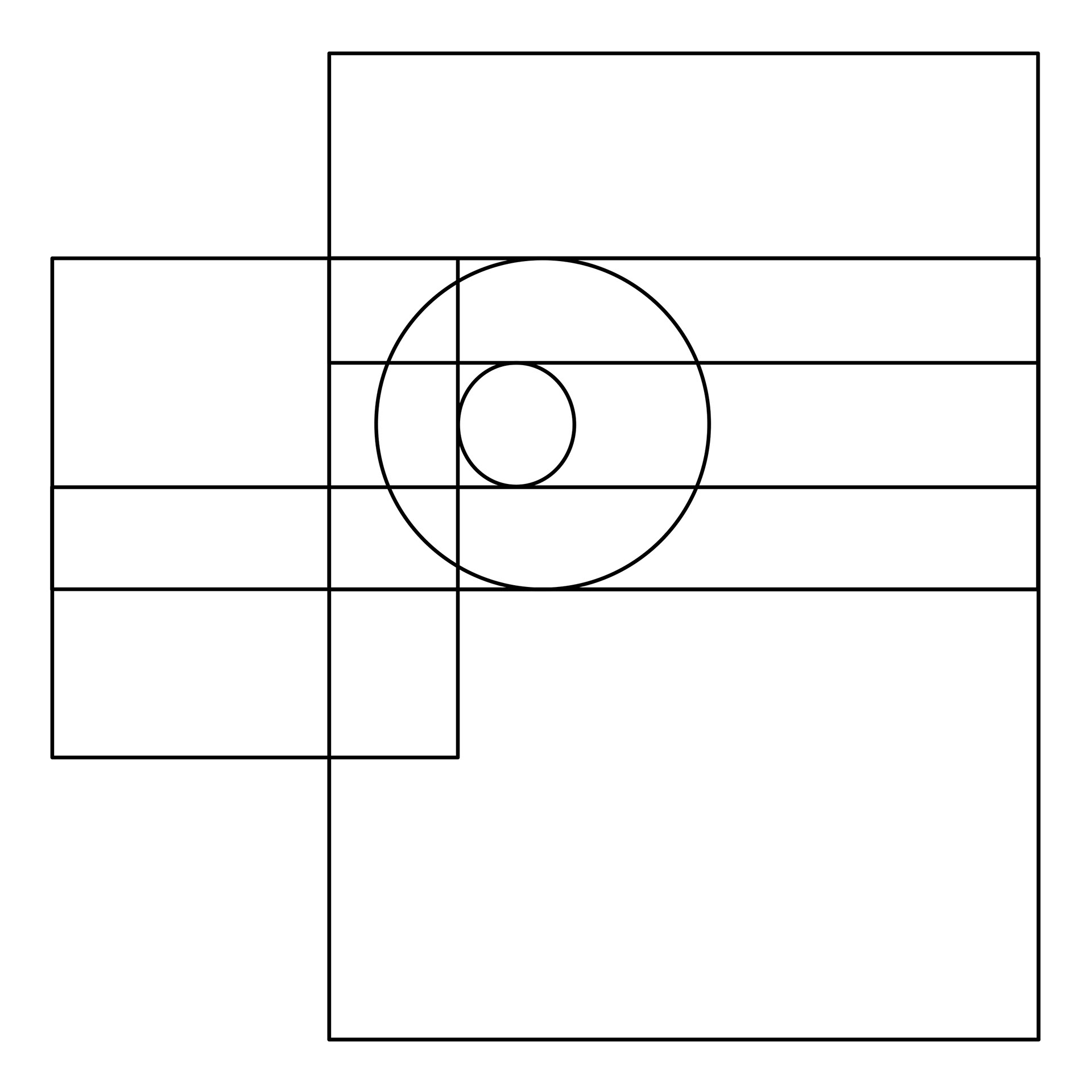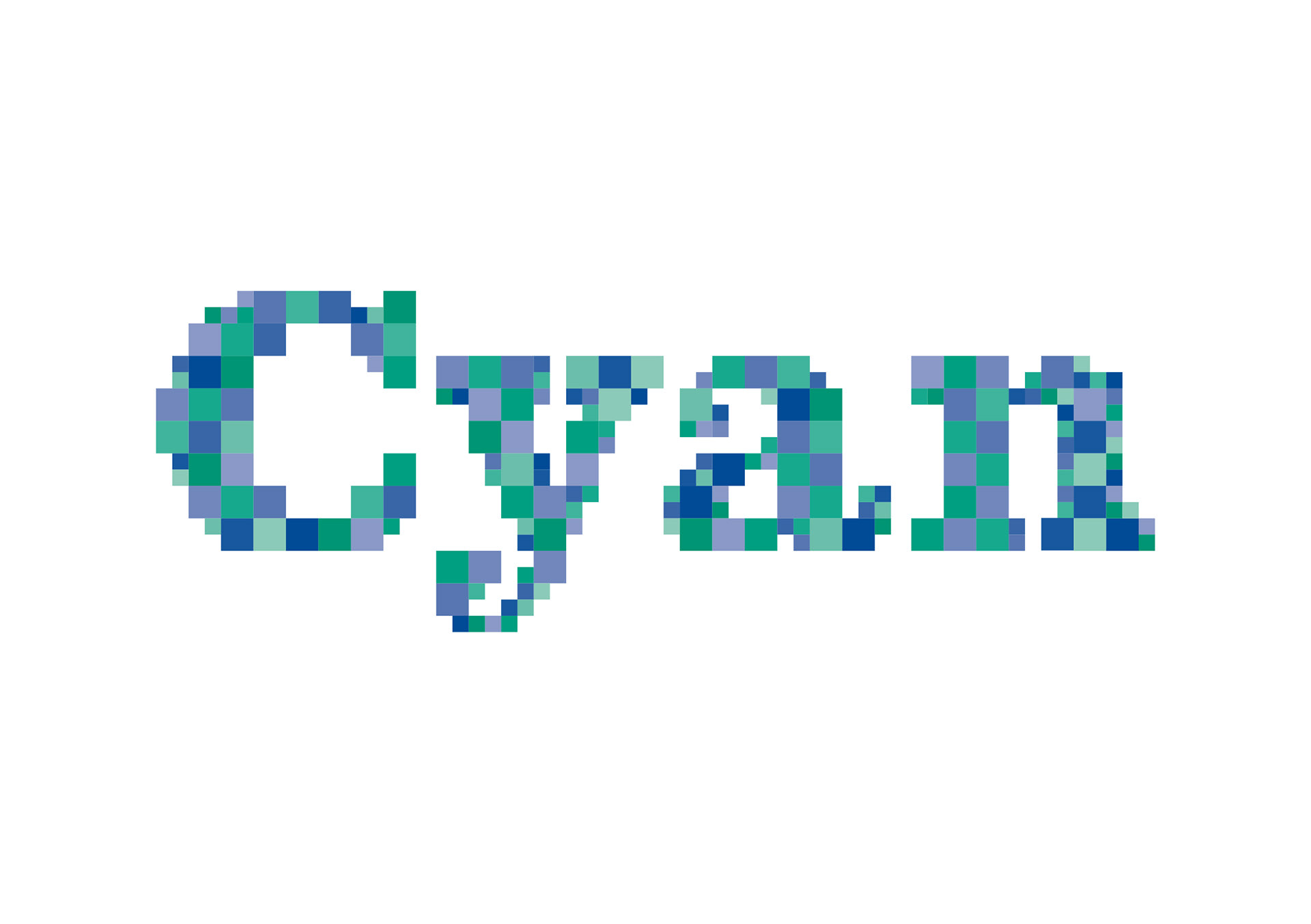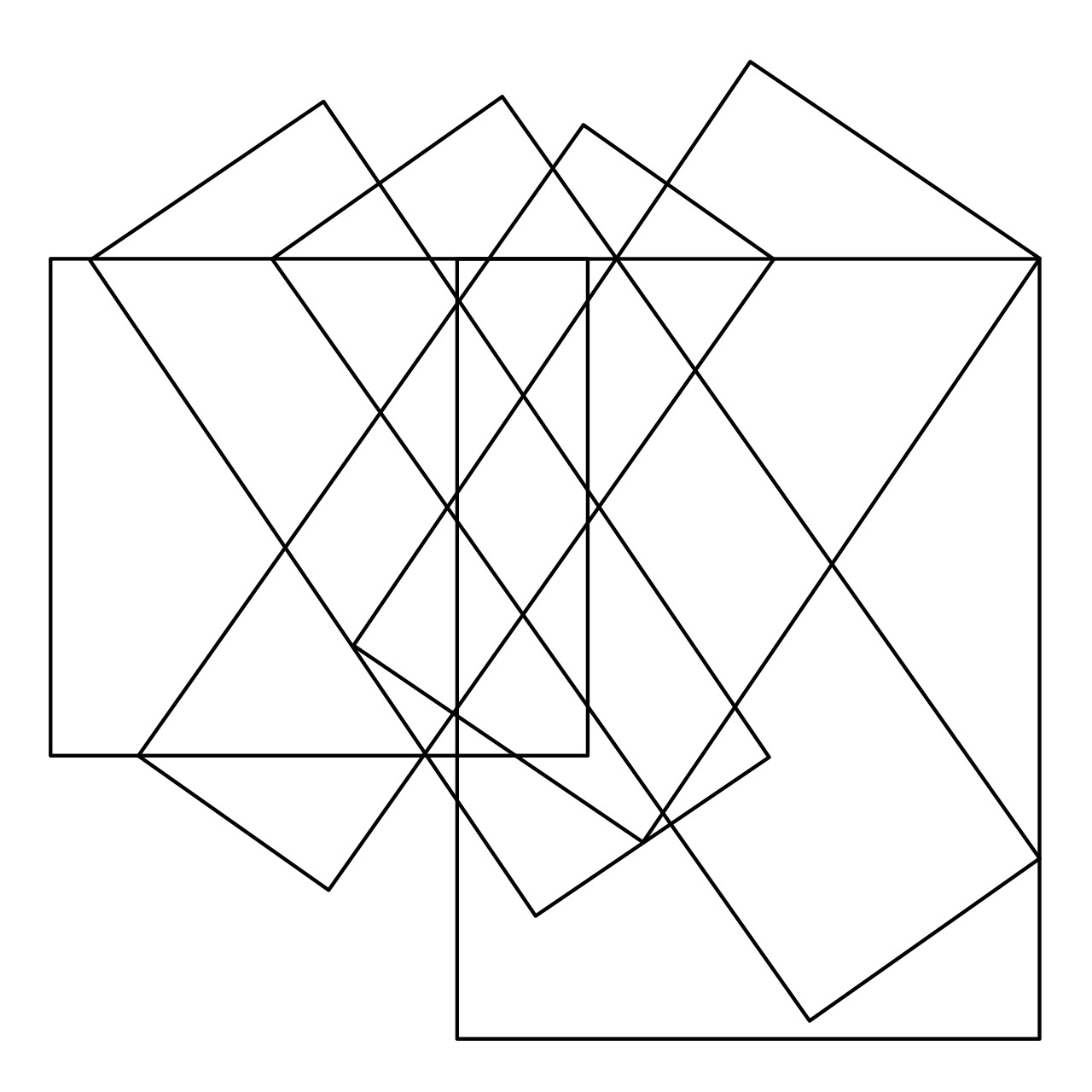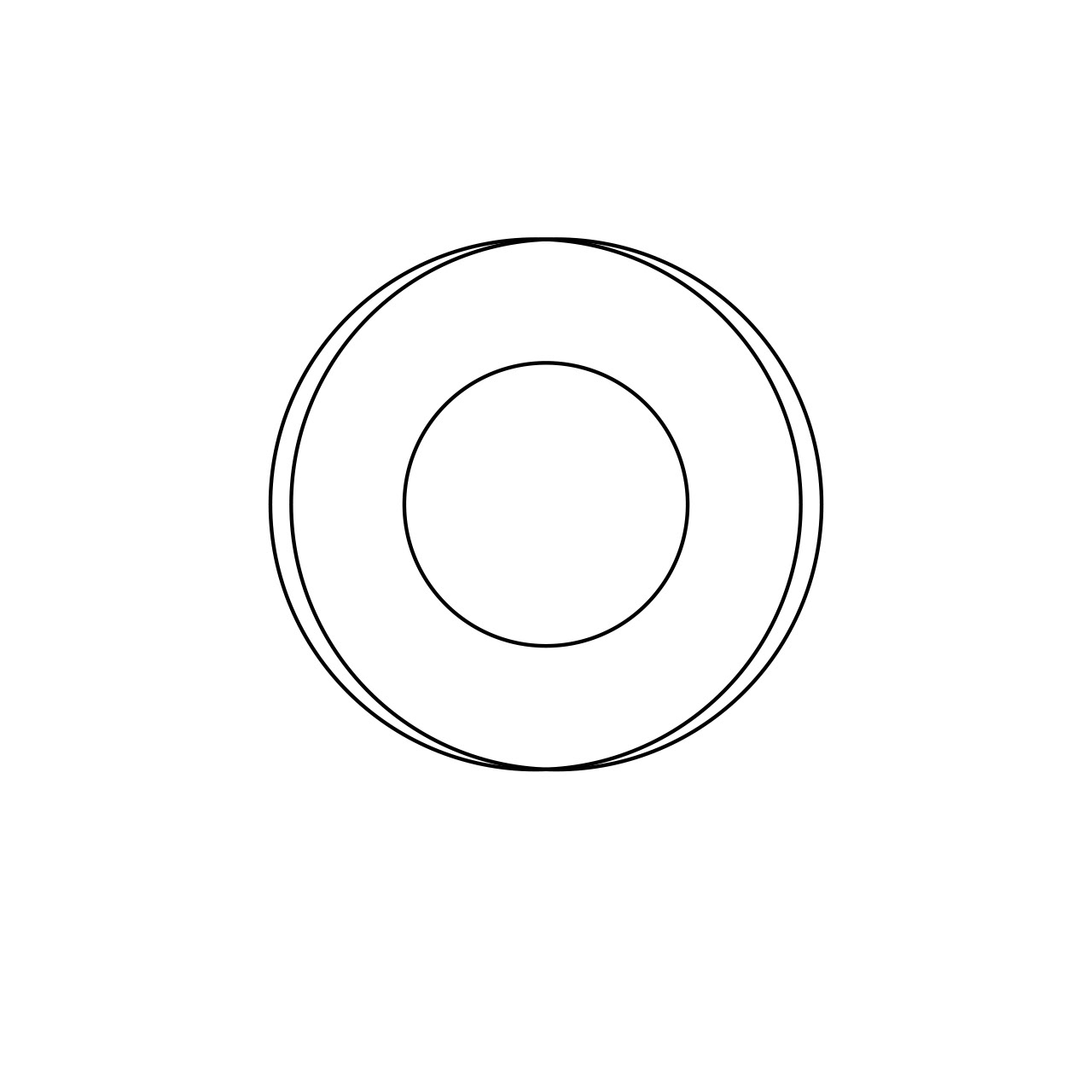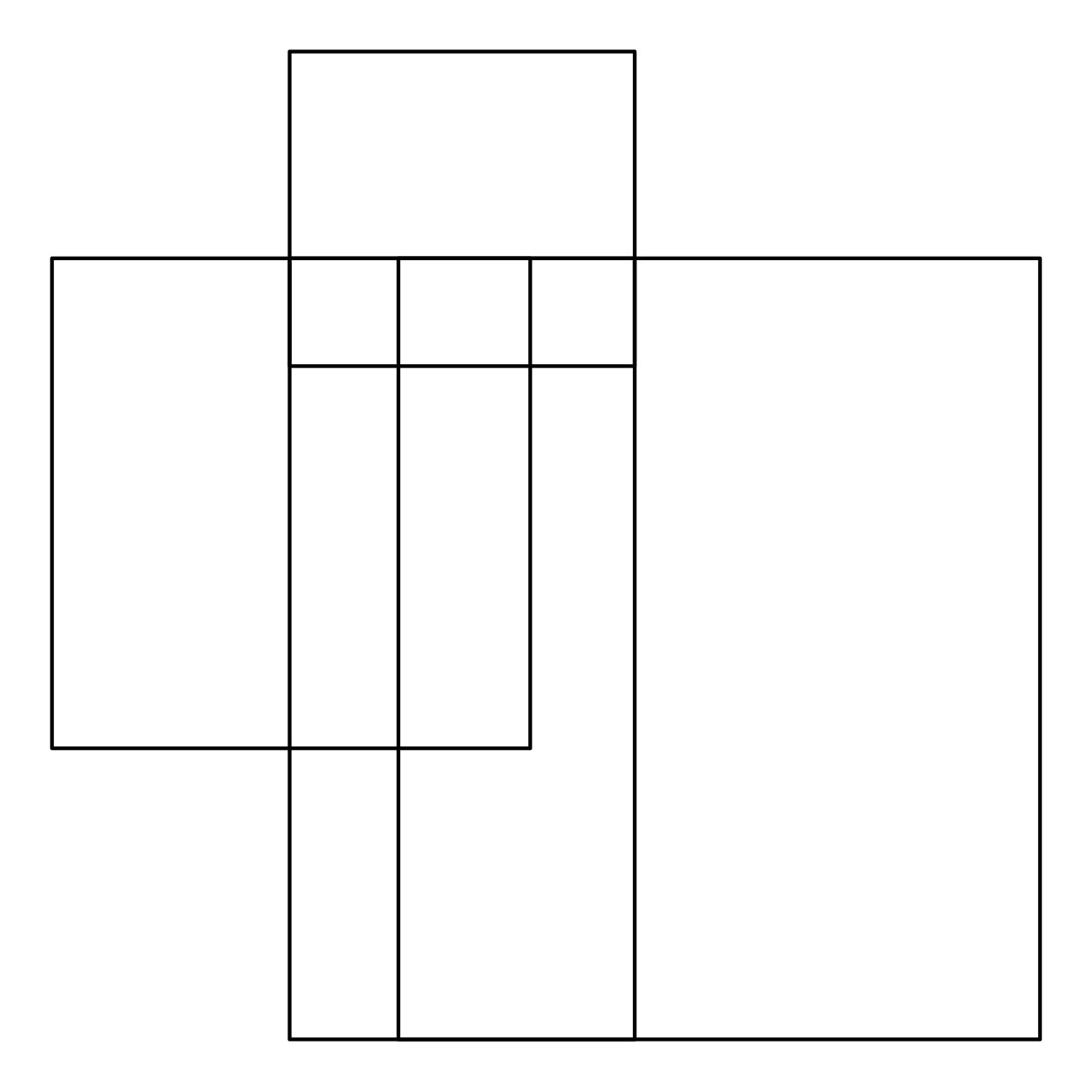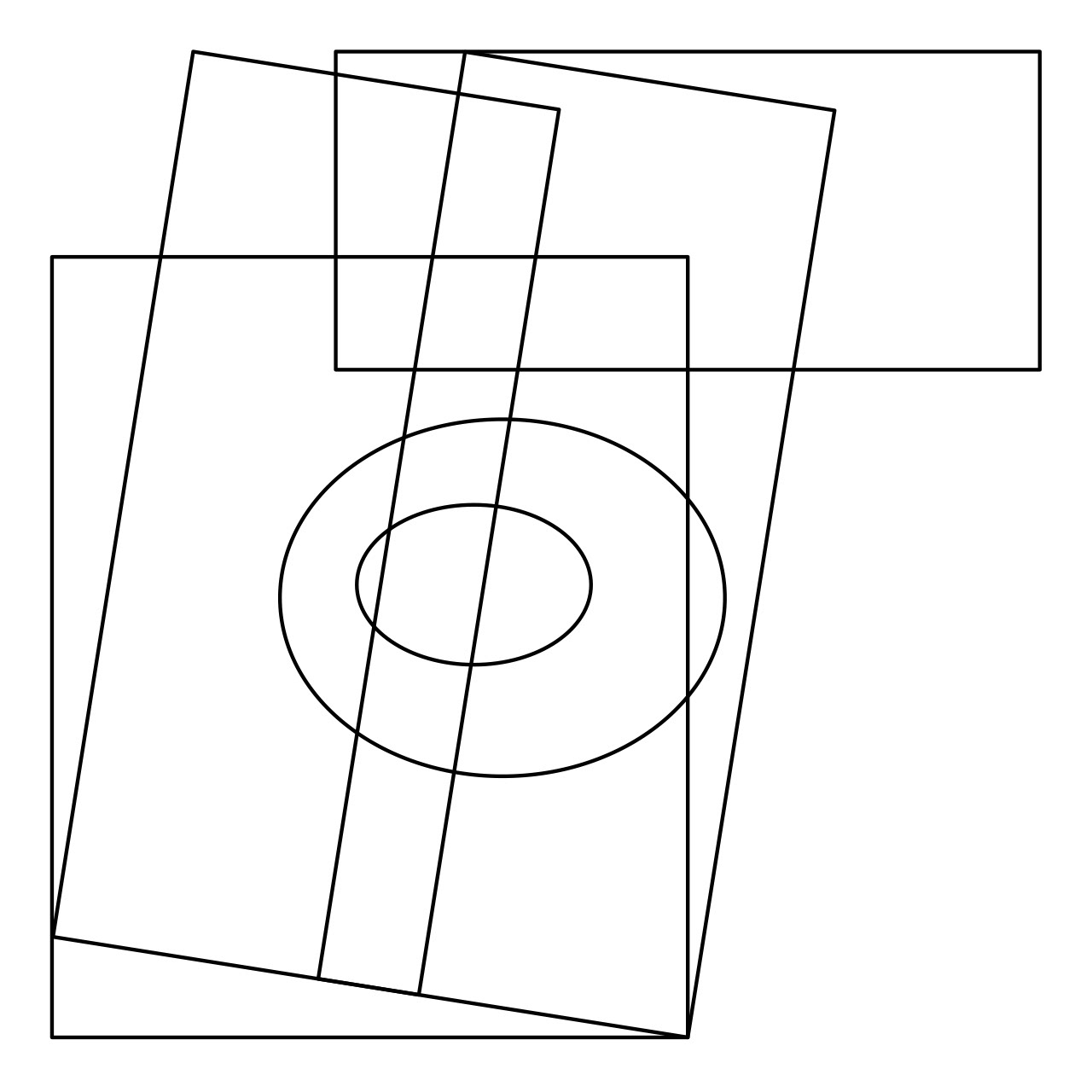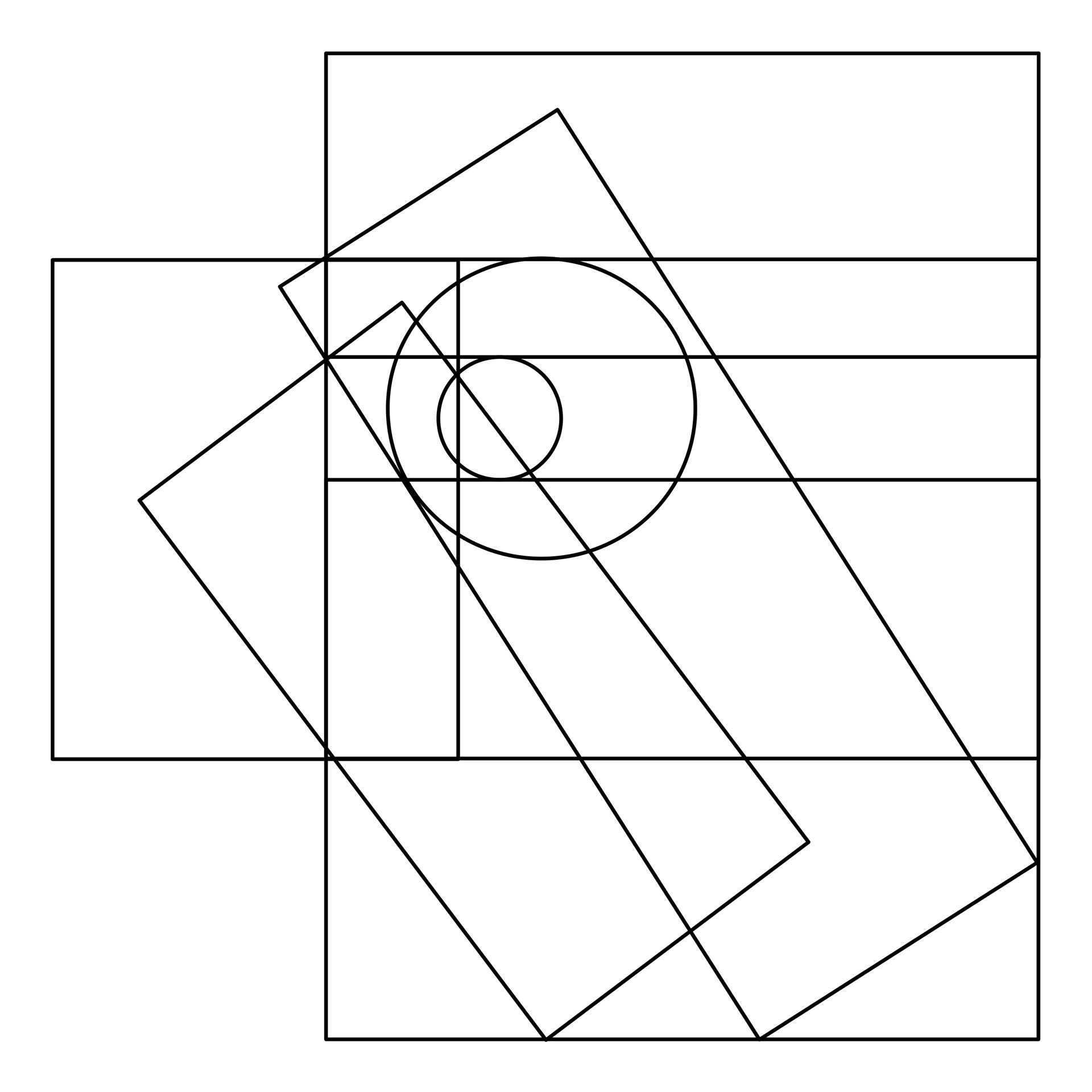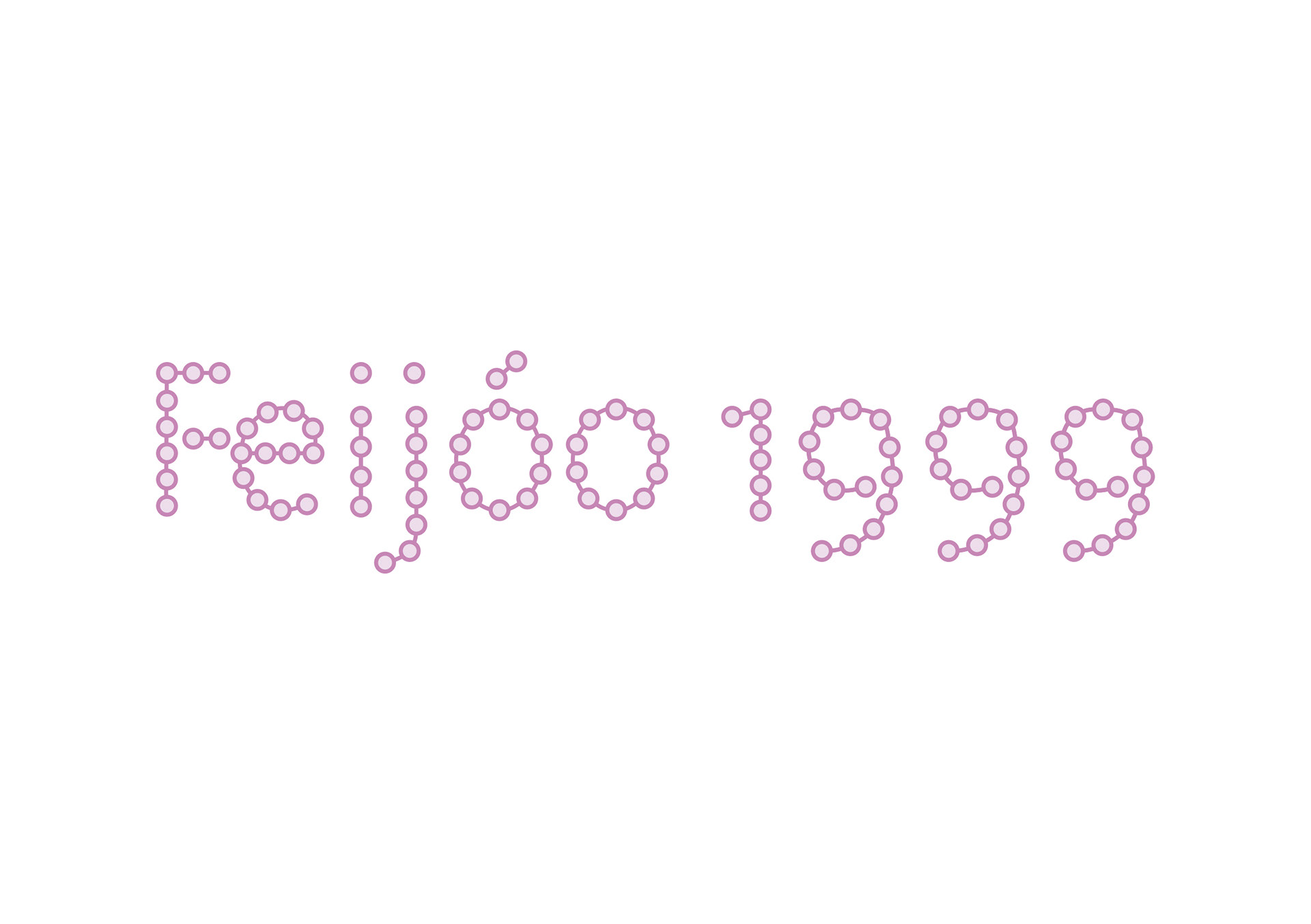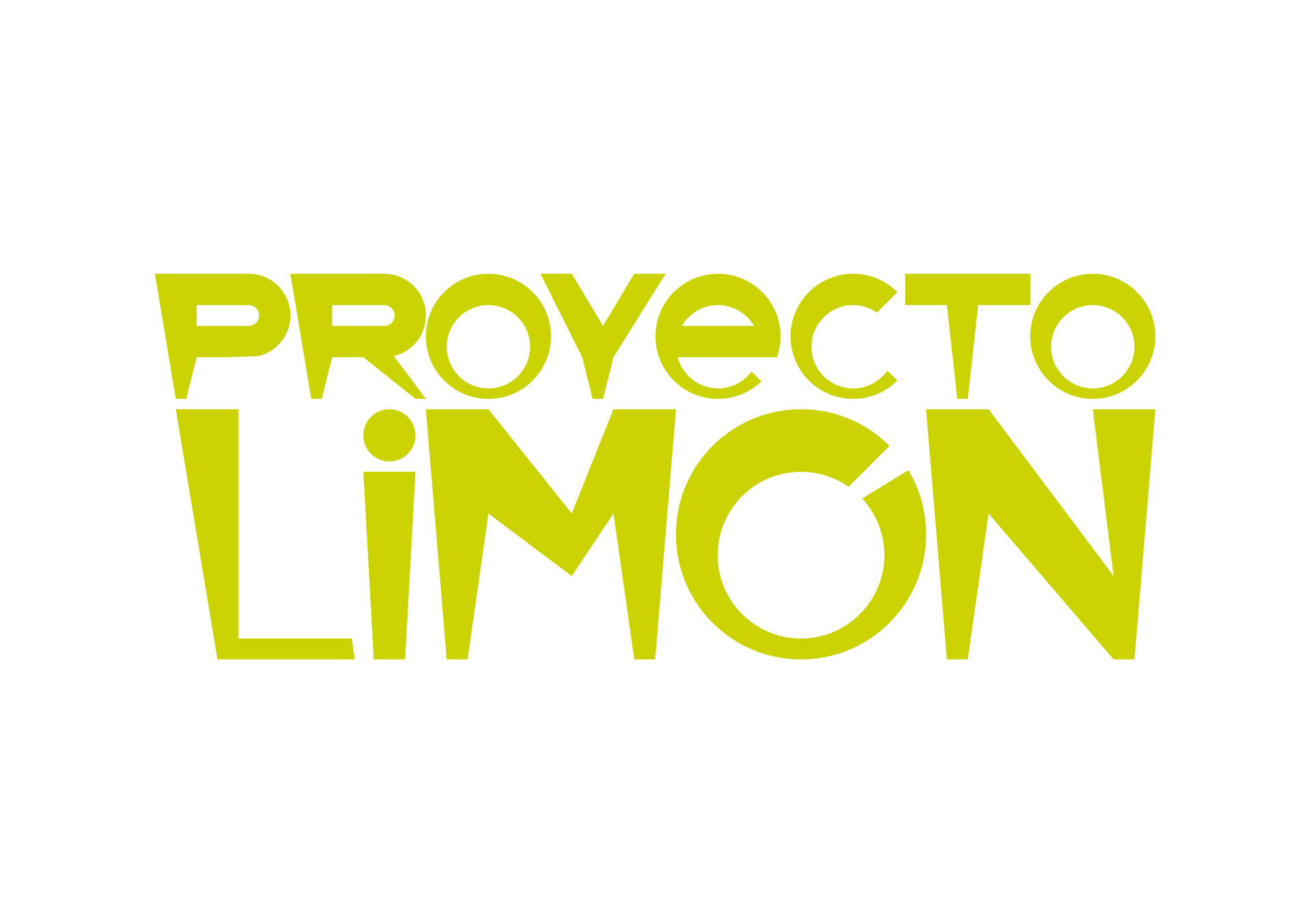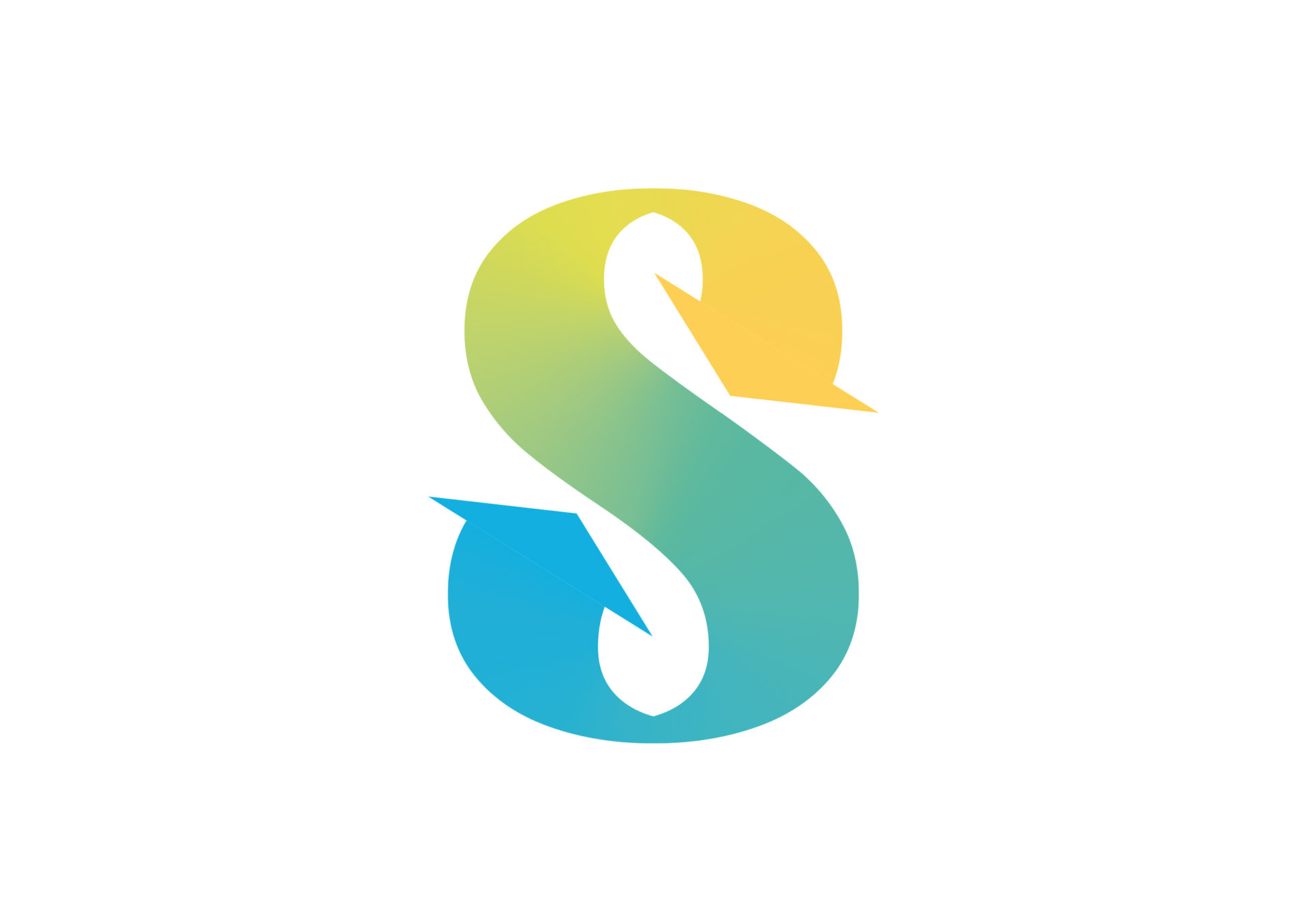
"La mode est un langage sans mots. C'est une forme d'expression qui s'exprime à travers les tissus, les couleurs et les silhouette, tout comme les mots d'un poème ou d'un roman" Coco Chanel
Propuesta para Slanted Magazine #44 — TYPE FASHION, 2024
N·E. By Nova Estetic
Logotipo para salón de estética, 2021-22
36 DAYS OF TYPE
36days es un proyecto que invita a diseñadores y artistas gráficos para que aporten su visión particular de los signos que forman nuestro alfabeto.
S
Propuesta de icono, 2018
Cliente: BeSolar
Alfabeto Chapapote, 2003-2011
Organic
Propuesta de símbolo, 2009
Feijóo 1999
Logotipo, 2005
Cliente: Feijóo 1999 (importación para mayoristas de perlas y piedras preciosas)
Cyan
Propuesta de logotipo, 2004
Con únicamente dos tintas se consigue un efecto cromático excepcional
Proyecto Limón
Logotipo, 2002, 2019
Publicado en Marcas & Trademarks de Quim Larrea, editorial Gustavo Gili.
Alfabeto Disomag